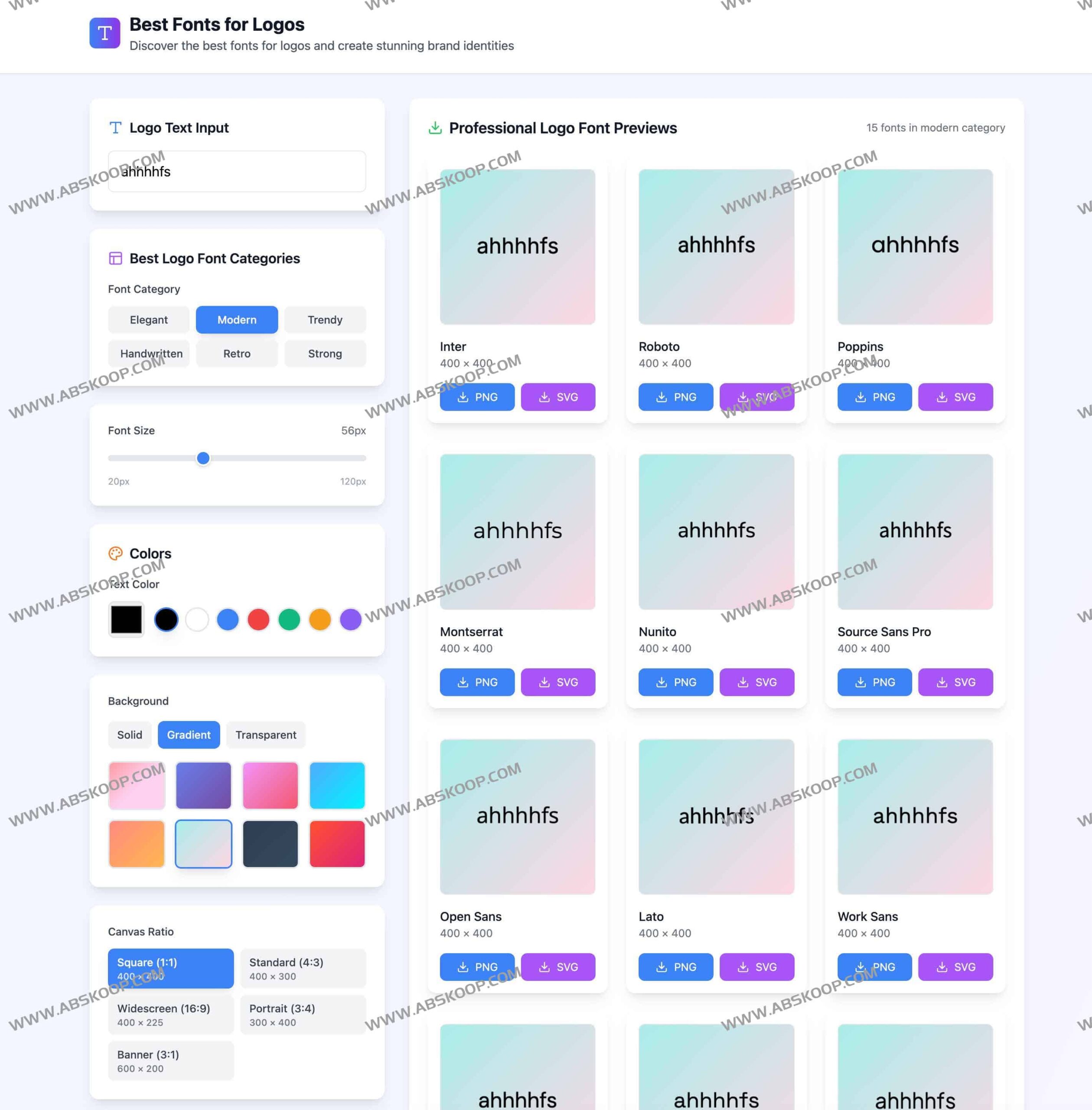
Best Fonts for Logos:极简在线 Logo 生成工具
Best Fonts for Logos 是一款主打高效、低门槛的在线字体 Logo 生成器。它将复杂的品牌设计流程简化为“输入文字、挑选字体、调整配色”三个步骤,让没有任何设计基础的用户也能在几分钟内快速构建出具有专业感的品牌标识。
核心功能与优势
• 零门槛快速出图 :采用线性工作流(输入 $rightarrow$ 选体 $rightarrow$ 调色 $rightarrow$ 生成),大幅缩短设计周期。
• 多风格字体库 :内置涵盖现代简约、经典端庄及创意前卫等多种风格的字体,满足不同品牌调性。
• 专业导出格式 :支持 PNG 透明背景 (适用于网页和社交媒体)以及 SVG 矢量格式 (适用于无损放大和商业印刷)。
适用场景
• 电商与独立站 :为新上线的商品或店铺快速创建品牌视觉符号。
• 初创团队 :在项目 MVP 阶段,以极低成本快速建立初步的视觉识别系统。
• 自媒体创作者 :为个人频道、社交账号制作高辨识度的文字 Logo。
• 个人开发者 :快速解决个人项目或开源工具的 Logo 需求。